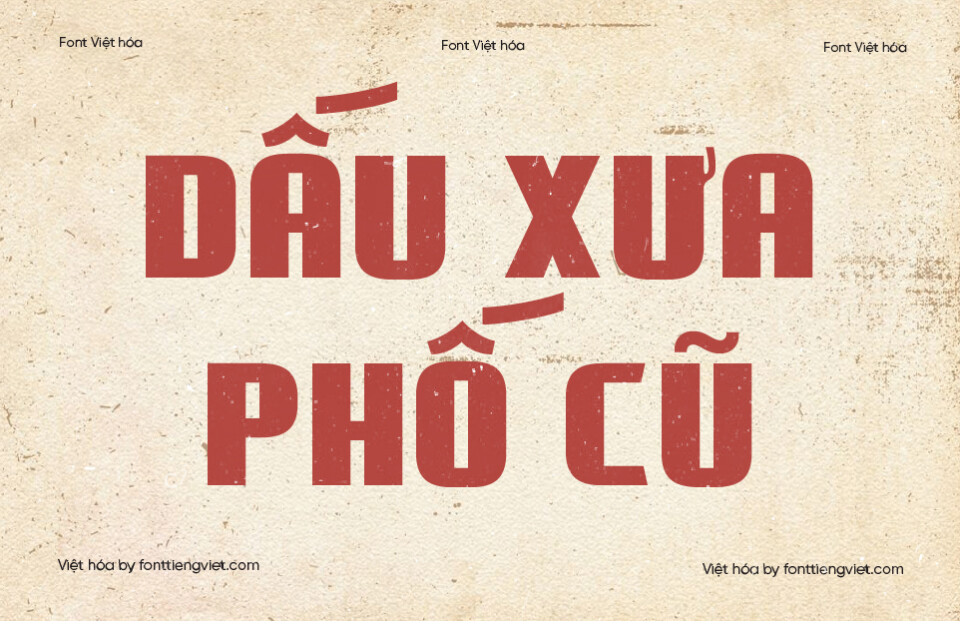
Font Việt hóa 1FTV Huxley Max ExtraBlack – Font Không Chân Cứng Cáp Cho Quảng Cáo
Trong lĩnh vực thiết kế đồ họa hiện đại, việc lựa chọn Font Chữ đóng vai trò then chốt để tạo nên sức hút cho thông điệp truyền thông. Font Việt hóa 1FTV Huxley Max ExtraBlack – Font Không Chân Cứng Cáp Cho Quảng Cáo là một lựa chọn tiêu biểu dành cho các nhà thiết kế đang tìm kiếm sự mạnh mẽ và chuyên nghiệp. Với độ dày nét vượt trội, bộ font này mang đến cảm giác vững chãi, giúp các tiêu đề quảng cáo trở nên nổi bật và dễ nhận diện ngay từ cái nhìn đầu tiên.
Ưu điểm của Font Việt hóa 1FTV Huxley Max ExtraBlack – Font Không Chân Cứng Cáp Cho Quảng Cáo
Thiết kế không chân hiện đại
Huxley Max ExtraBlack sở hữu phong cách sans-serif tối giản nhưng đầy uy lực. Các đường nét được gọt giũa vuông vức, loại bỏ những chi tiết rườm rà để tập trung tối đa vào cấu trúc chữ. Điều này giúp bộ font duy trì được sự rõ ràng ngay cả khi sử dụng trên các biển quảng cáo ngoài trời có kích thước lớn hoặc các biểu ngữ kỹ thuật số.
Tối ưu cho mục đích truyền thông
Đúng như tên gọi, đây là dòng font được đo ni đóng giày cho ngành quảng cáo. Với trọng lượng ExtraBlack, font chữ này tạo ra độ tương phản cực cao trên mọi nền màu. Sự cứng cáp của nó rất phù hợp với các chủ đề về công nghệ, thể thao hoặc các sự kiện cần khẳng định vị thế thương hiệu mạnh mẽ.
Ứng dụng Font Việt hóa 1FTV Huxley Max ExtraBlack vào thực tế
Người dùng có thể ứng dụng font này vào việc thiết kế poster, banner website hoặc làm typo cho các video marketing sinh động. Việc đã được Việt hóa hoàn chỉnh giúp các bạn học sinh và giáo viên dễ dàng sử dụng trong các bài thuyết trình hay ấn phẩm trường học mà không lo lỗi dấu tiếng Việt. Hãy trải nghiệm ngay Font Miễn Phí, Font Việt Hóa, Font Việt hóa 1FTV Huxley Max ExtraBlack – Font Không Chân Cứng Cáp Cho Quảng Cáo để nâng tầm chất lượng cho các dự án sáng tạo cá nhân của bạn một cách hiệu quả và chuyên nghiệp nhất.